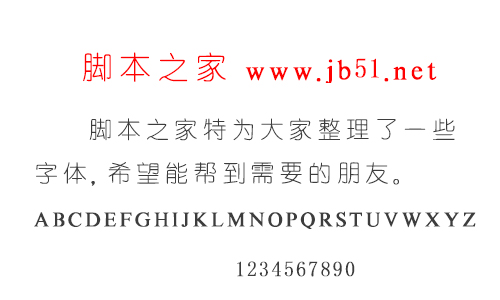
蘭米細(xì)圓是蘭米字庫(kù)推出的一款經(jīng)典細(xì)圓體,字體工整簡(jiǎn)潔,具有強(qiáng)烈的視覺(jué)沖擊力,適應(yīng)于報(bào)紙和雜志和書(shū)籍中常用字體, 海報(bào)、個(gè)性促進(jìn)品牌標(biāo)志設(shè)計(jì)、字體設(shè)計(jì)、等環(huán)境使用,歡迎喜歡蘭米細(xì)圓字體的朋友前來(lái)下載使用。